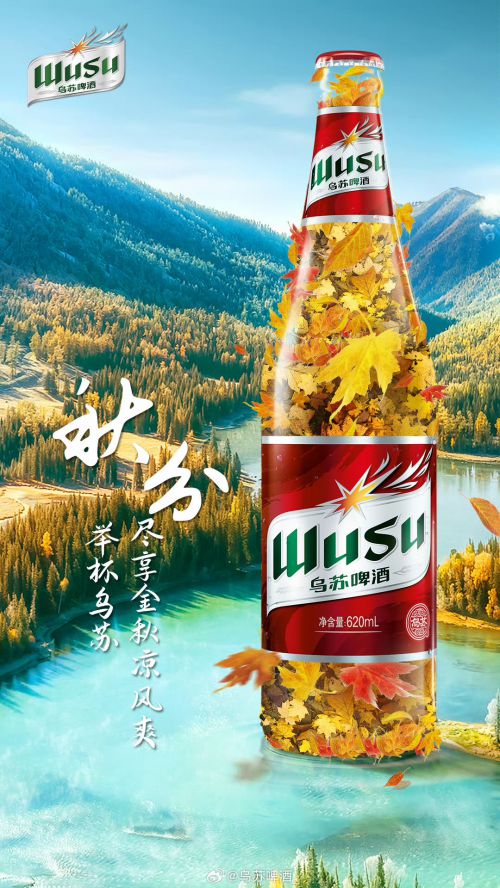
演示悠然小楷
### 悠然小楷:传统小楷书法字体,以“悠然”气质传递东方笔墨韵味 悠然小楷是一款融合传统书法底蕴与现代设计需求的小楷字体,字形修长舒展,重心平稳居中,中宫松紧适中——既保留小楷书法的端庄骨架,又通过纵向拉伸的比例增添几分灵动气韵,整体结构疏密有致,耐看且易读。 字体笔型设计尤为出彩:笔画纤细圆润,圆头收笔自带毛笔书写的温润质感,起笔轻缓、行笔流畅,转折处柔和无棱角,尽显手写书法的自然韵律。粗细均匀的线条搭配断开式笔画连接,让字体在精致中透着呼吸感,避免密集排版的刻板,反而如文人挥毫般从容“悠然”。 无论是古风海报、书法作品集内文、文化类书籍标题,还是雅致邀请函、传统节日宣传物料,悠然小楷都能以其独特的“悠然”气质,将毛笔笔墨的生动韵味注入版面。它不仅是一款字体,更是传统东方美学的载体,用纤细圆润的笔触,为设计传递沉静、温润、富有书卷气的视觉语言。